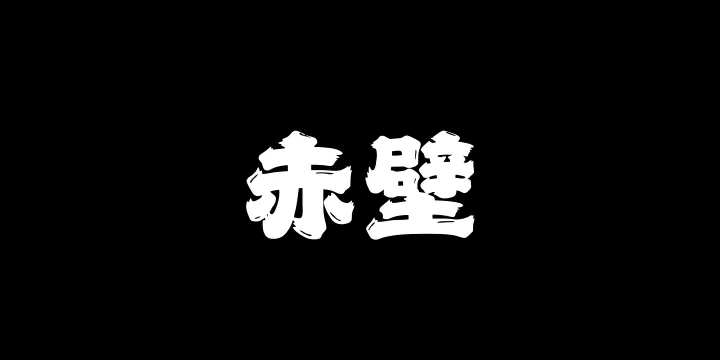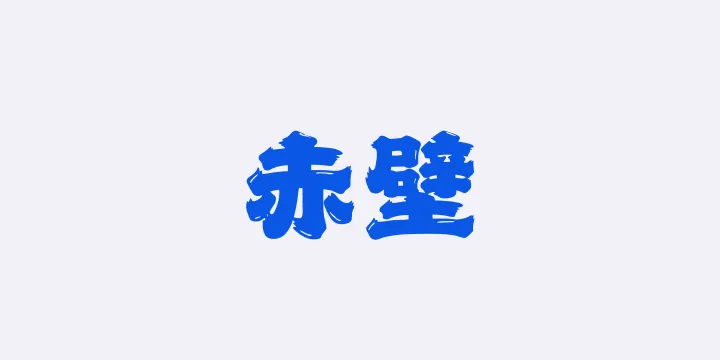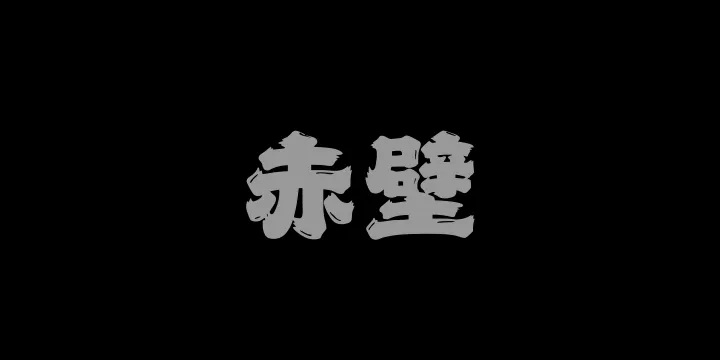
字体全名: 山海赤壁W
字体简介: 山海赤壁,包含简繁汉字9169个,是一款大字榜书的隶书风字体。该字体雄健有力,非常醒目!融入楷书特点,有力、宽厚、方正,如同巍峨的大山,充满了稳重感和设计感。古朴浑厚,笔画与字形间透露着榜书的古雅和刚劲的特点,在浑厚的同时而又极富张力,桀骜不驯的特性,霸气外露。它的笔画充满力量感,组合搭配极富强烈的节奏感。在粗细的纵横间,拥有非常规的张力特性。